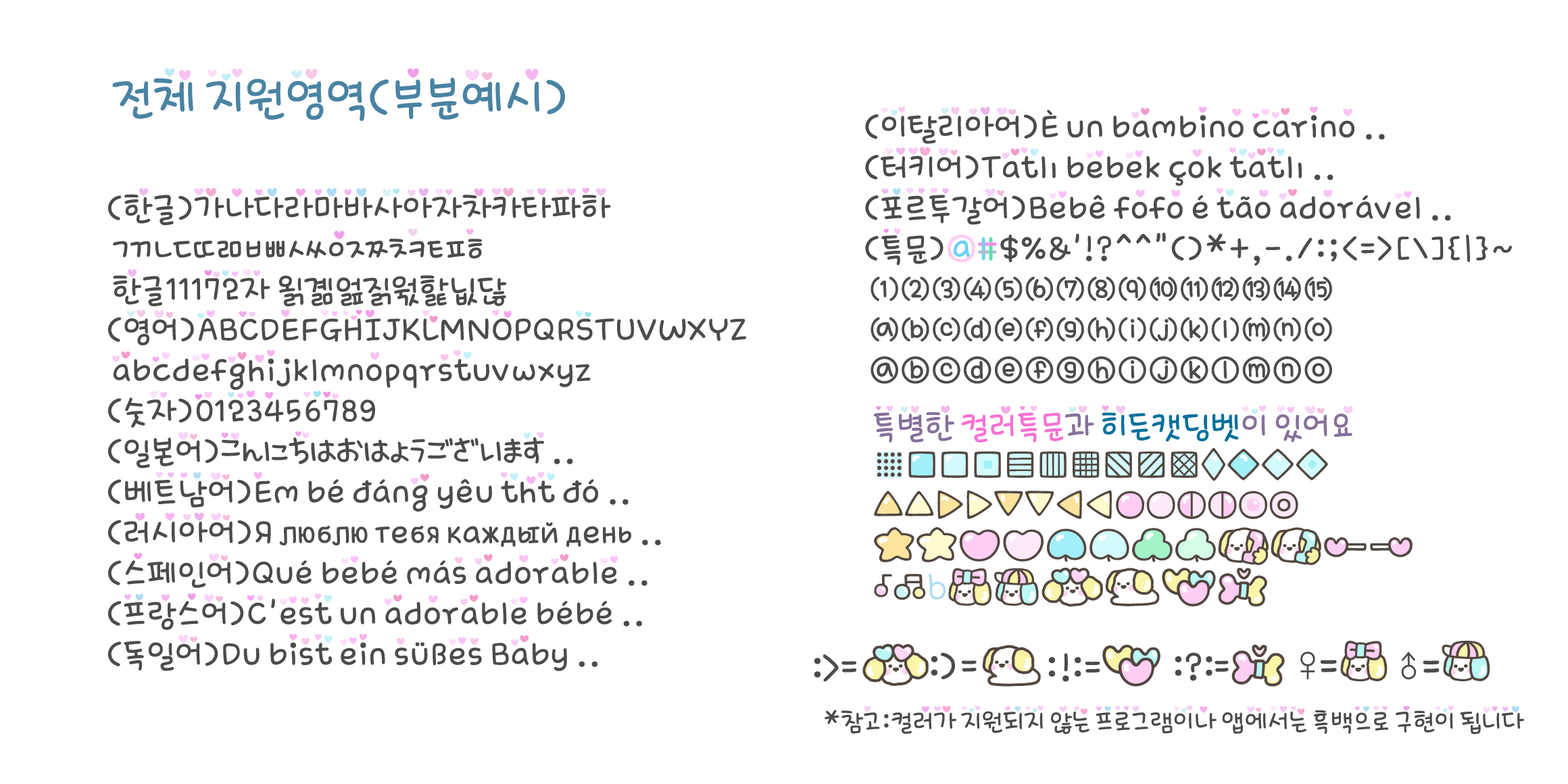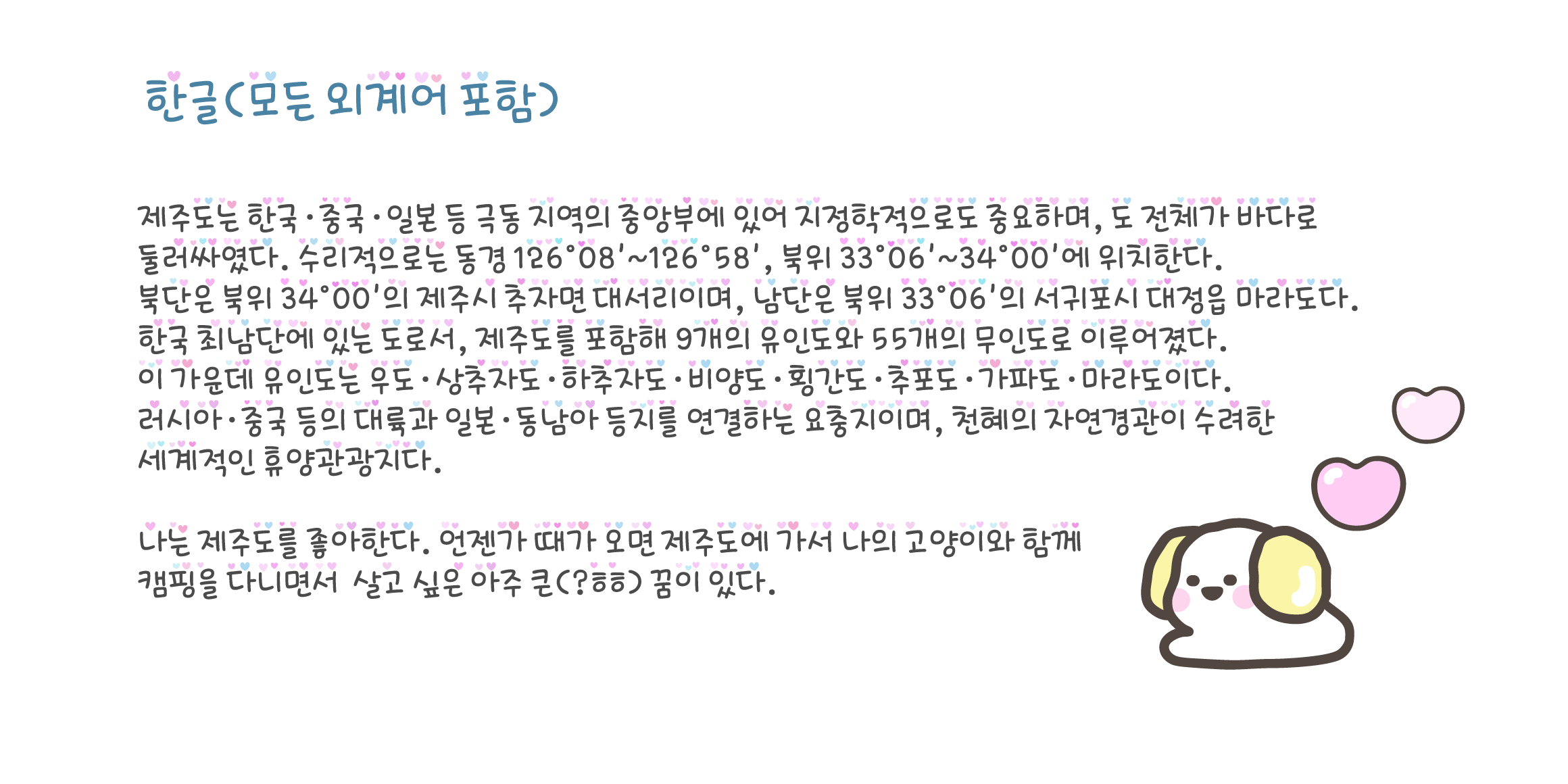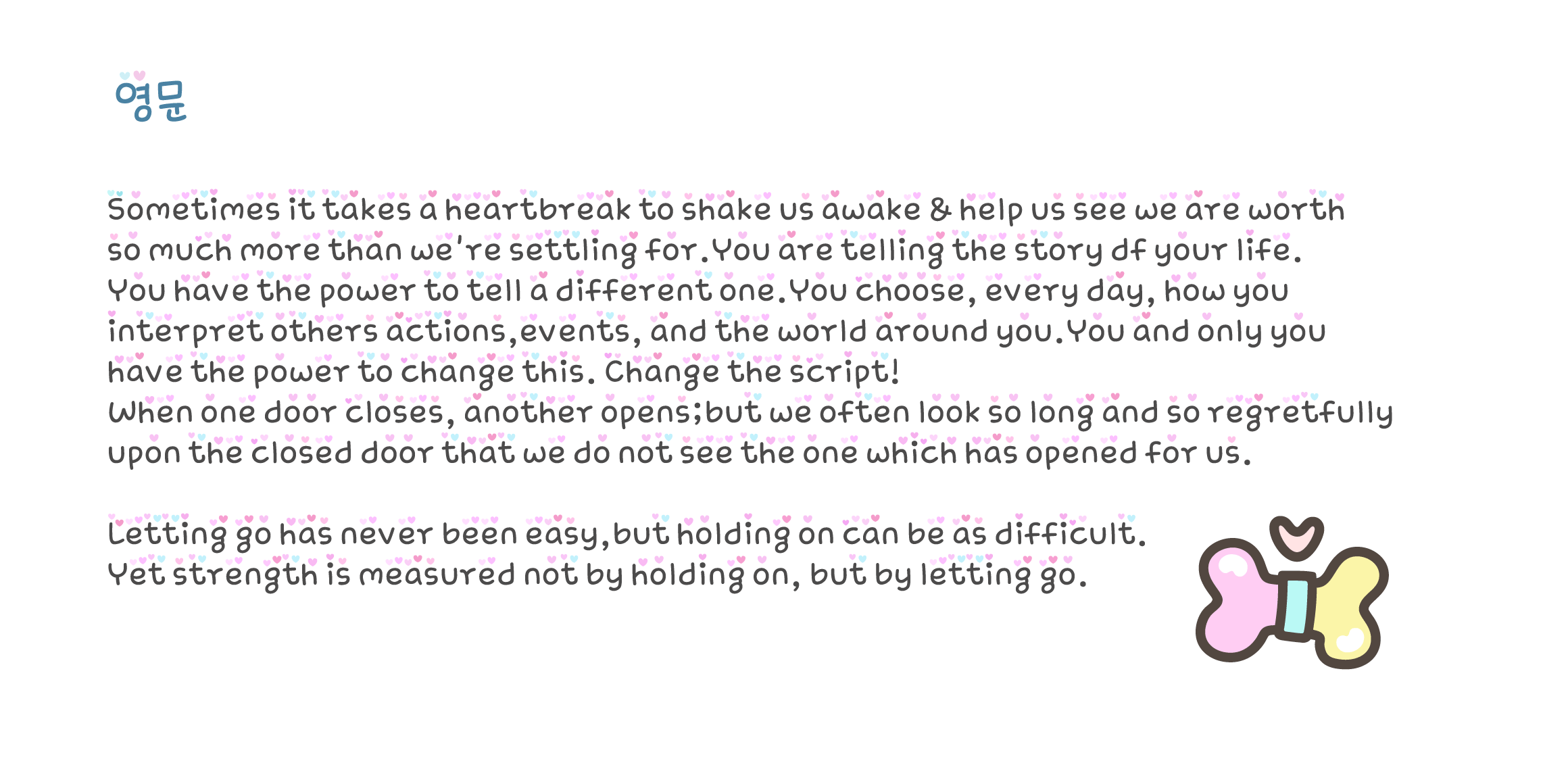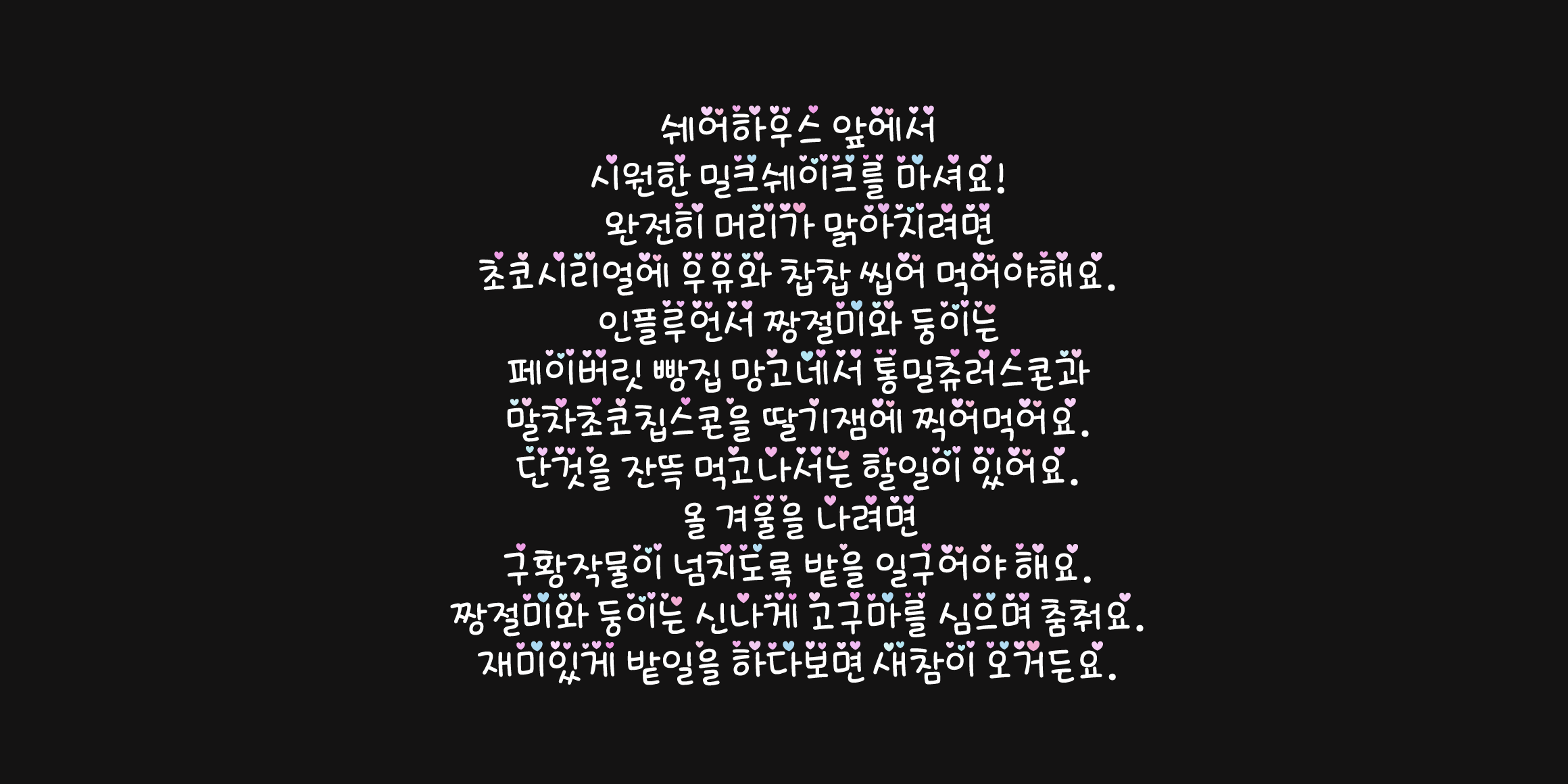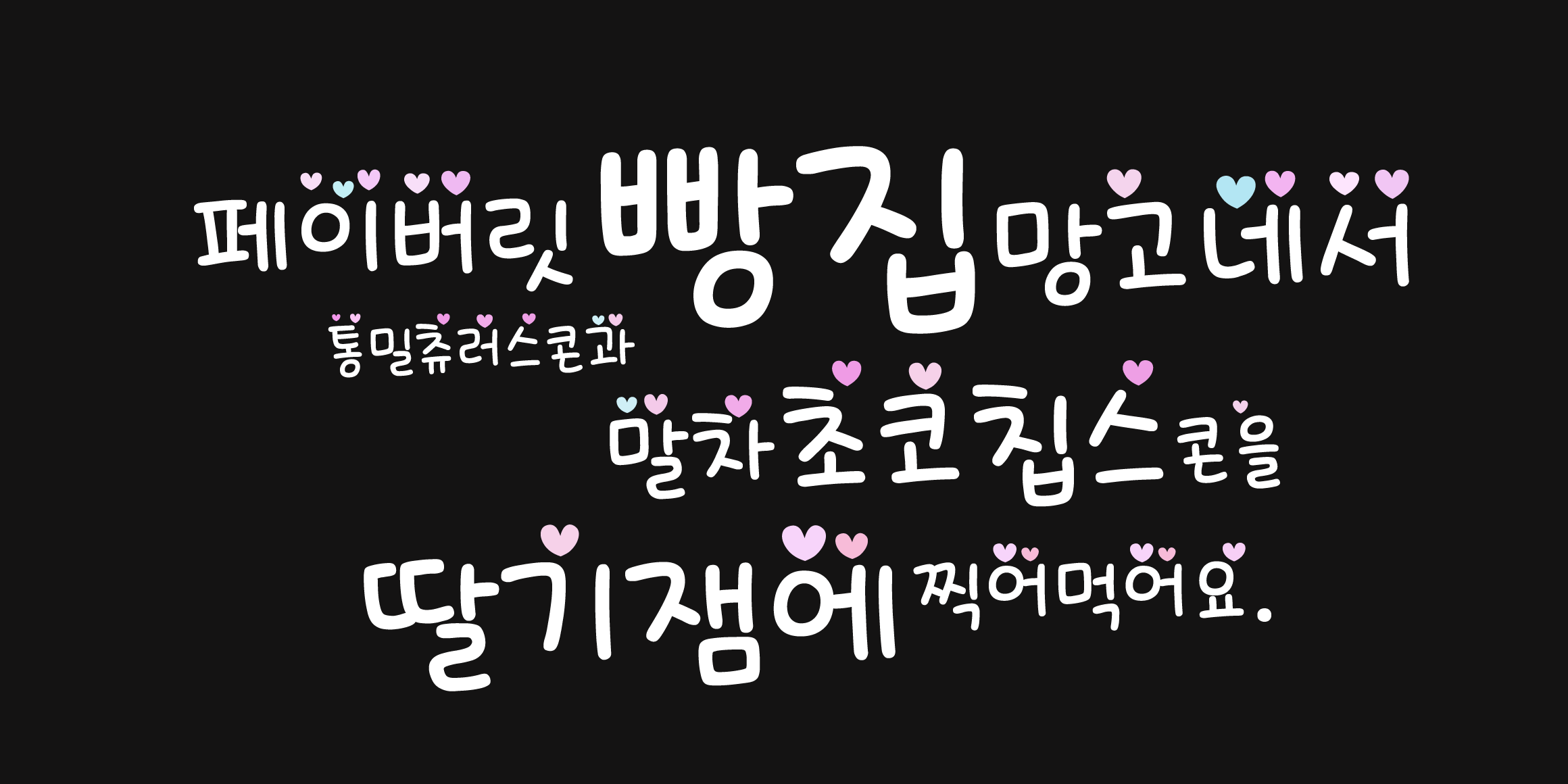
(캣폰트 시즌2 입니다)
솜사탕처럼 부드럽고 하얀 털을 가진 아기 댕댕이가
꿈속에서 핑크하트가 가득한 세상을 만나는
장면을 상상하며 만든 폰트입니다.
글자위에 하트가 우수수 떨어집니다.
문득 외로움을 느낄 때
다크모드로 변경해서 폰 글꼴을 써 보시면
조금은 위로가 되실 거예요!
♥키보드 ; > ; ) : ! : : ? : 을 연달아 치면
매력적인 캣딩벳이 나타납니다.
♥영어 일어 베트남어를 포함한
독일 프랑스 러시아 이탈리아 포르투갈 스페인 터키 등
유럽의 다양한 국가들의 언어도 함께 지원하는 등
폭넓은 언어와 특수문자 지원을 합니다.
♥캣폰트의 디자인은 오랜 시간 연구한 결과물입니다.
- Cat2하트댕이 / Cat2HeartPuppy